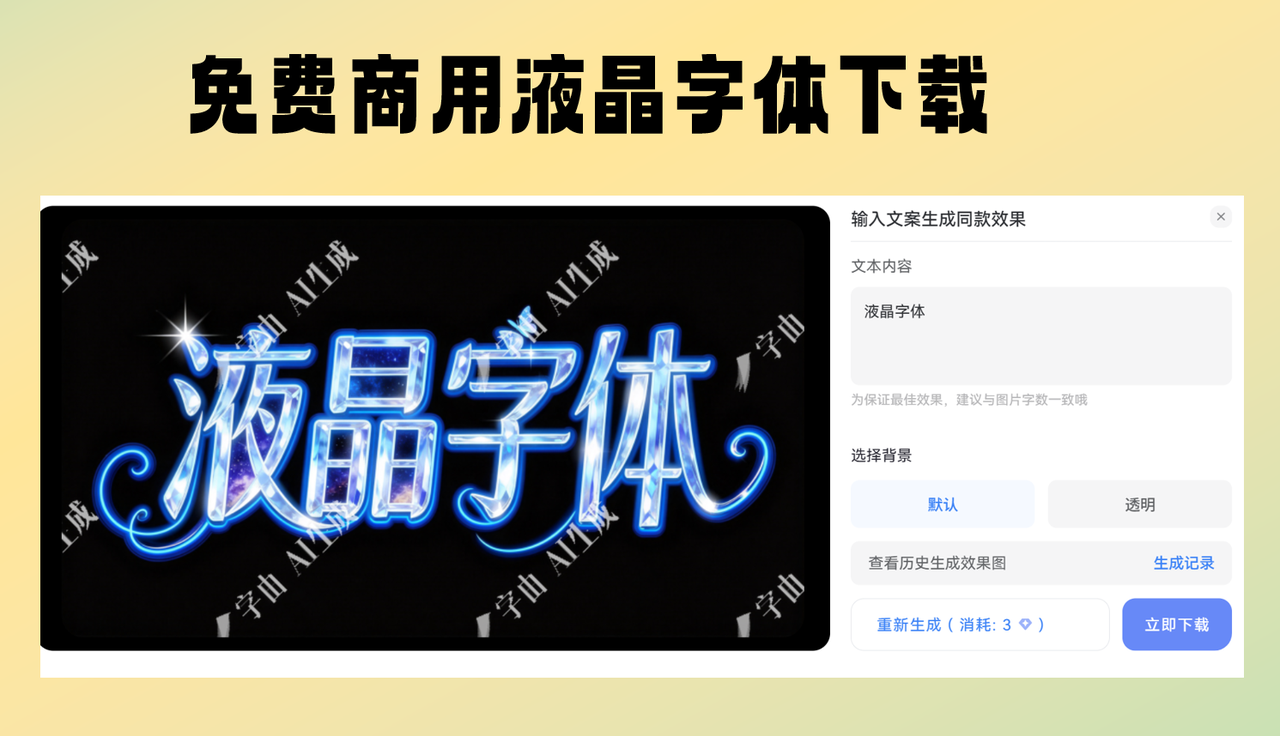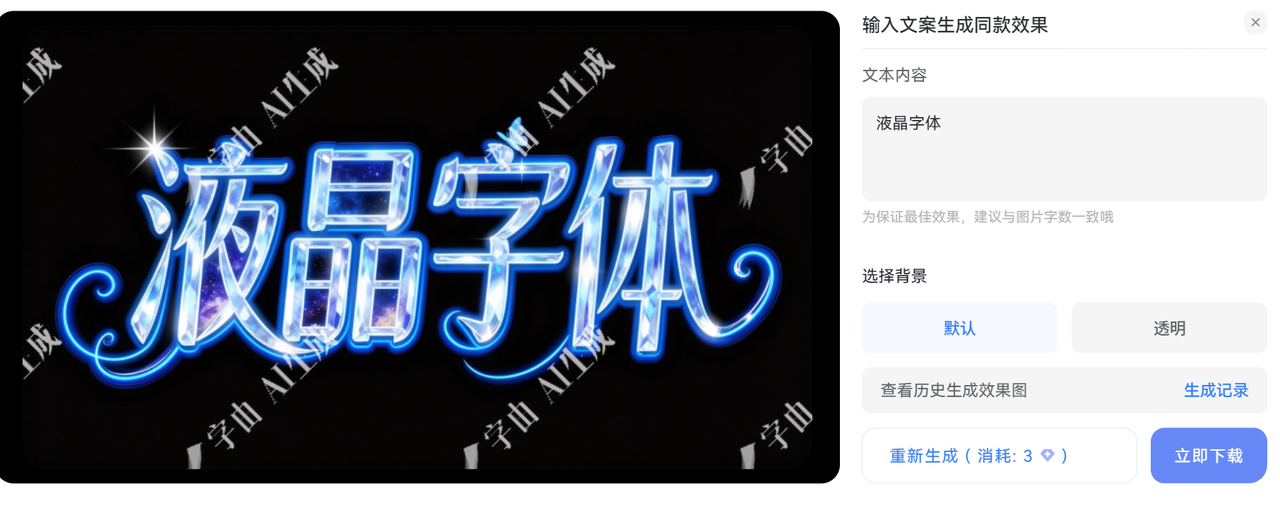
免费商用液晶字体下载指南,实用AI工具与优质字体平台推荐
在设计项目中,选择合适的字体至关重要。尤其是液晶风格字体,因其独特的科技感和未来感,越来越多设计师和内容创作者青睐于此。本文分享几个既免费商用的液晶字体资源平台。
什么是液晶字体?
液晶字体通常带有点阵、像素化或光栅化的视觉效果,模仿液晶显示屏的数字和字母样式。它们常用于科技、电子产品、游戏界面和未来感设计中。液晶字体给人一种现代感和技术感,能够让设计作品更具吸引力。
字由 AI 字体工具
最近,我发现了一个方便的工具——字由 AI 字体工具。它不仅提供免费的液晶字体下载,还能利用人工智能帮你定制字体设计。
AI字体设计工具的特点:
- 操作简单:无需专业设计基础,只需输入文字内容,选择液晶字体风格,几秒钟生成专属字体。
- 多样风格选择:液晶点阵、像素风、数字显示风格一应俱全,满足不同视觉需求。
AI 生成液晶字体教程
在线打开AI生成字体工具页面,在风格分类下,选择“冰晶”。
选择一个模板,输入想要做成液晶字体的文字,点击一键生成即可
通过HelloFont的液晶字体AI生成工具,我能快速获得符合视觉需求的字体设计,省去了自己绘制或挑选的时间。结合其他平台的资源,我建立了一个稳定的字体素材库,满足工作中多样的设计需求。